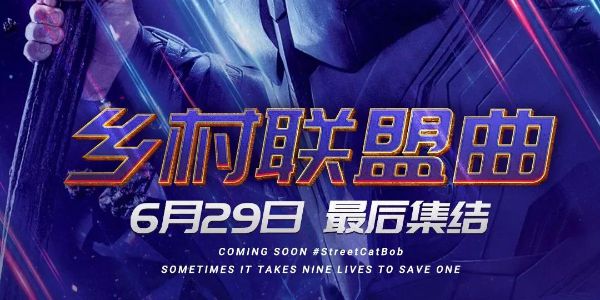
新媒体设计排版教程,新人必看的新媒体排版宝典
说到公众号排版,我认为这是每一位新媒体编辑必备的基本技能。
无论是在校社团新媒体小白,还是新媒体工作者,相信大家对排版界面都不会陌生,同样的一个界面,大家排版出来的效果却又千差万别。
去年陆续写过几篇关于公众号排版的文章,都深受小伙伴们喜欢,可惜没持续性为大家体系化整理,或许让一些小伙伴等得望眼欲穿。
过年期间开始准备了一段时间,写下这篇字数超1W字,干货知识点多达百个的长篇系列推文——《新媒体 · 公众号排版宝典》。
本篇长文,涉及公众号排版理论知识普及,推文排版参数标准,实用排版技巧及工具推荐四大板块,以供大家选择性的阅读查看。
01.
学习排版前,我们需要了解的东西
随着公众号的日益盛行,越来越多的企业在招聘的时候也增加了公众号编辑这一项工作要求,这也使得公众号编辑逐渐成为与office并肩,成为了日常工作中常用的一项办公技能。
很多人会说,公众号排版不就是将原有的Word文档,简单的复制粘贴到平台上而已吗?
但其实这个想法是错误的,新媒体编辑很多时候是兼顾内容、包装、原创及运营多个方面的一份工作。
以包装部分为例,主要工作就是为已有文案进行美化排版的过程,包括封面设计,文本排版、优化配图、banner、底部二维码、序号设计、分割线、历史原文等多个部分的排版。
公众号排版的作用
1. 保证推文美观流畅,减轻用户阅读压力。
用户阅读的时候往往是欣赏你的内容,但如果你的文章整篇都没有排版过,一长串密密麻麻,第一感觉会让人厌烦,没多少人会继续阅读下去。
2. 清晰传达文章有价值的信息,提高阅读效率
通篇文章如果没有将重点信息提取出来,用户阅读效率会很低,甚至容易错过关键信息,对标题、关键句等逻辑句进行排版,可以大大提高用户阅读效率。
3. 培养用户阅读习惯,加强对公众号品牌认知
我们每个人都会关注很多个公众号,如果每个推文的排版都千篇一律,那必然难以形成长远的品牌认知,但如果公众号能够提供给我们特定风格的排版,久而久之用户会产生依赖及习惯心理。
以一周进步、深夜发媸、杂乱无章为例,各自都有其特色的排版风格,对于用户而言会形成阅读习惯,阅读时会十分舒适。
一周进步主要内容为干货分享,图文以简约清晰排版,舒服地将实用内容传达给用户。
一周进步 · 排版样式
深夜发媸提供美妆时尚内容,排版风格往往设计感十足,从推文封面、内容排版到图片设计都充满了设计性,颜色往往比较吸引人,十分符合其平台定位。
深夜发媸 · 排版样式
杂乱无章的公众号排版,围绕主色调的蓝,文字做到清晰排版,很适合说故事表达观点,用户阅读下来没有太大压力。
杂乱无章 · 排版样式
通过优质的内容和独有的包装排版,能够让公众号在用户关注的同类型账号里形成独有的特色,从而提升整个公众号的形象。
排版前,需要思考的问题
公众号类型很多,所输出的内容也不一样,如果全部公众号都用统一的排版,那公众号便不存在“多样化”这一特性。
那么我们该如何优化公众号的排版呢,在这里我们可以问自己几个问题。
1. 你所需要排版的公众号是什么风格?
当我们需要优化一个公众号排版的时候,我们主要要考虑两个维度:行业和用户。
首先是行业,不同行业的公众号,在排版方面都会不太一样,从图片、文字到整体阅读体验,侧重点都因号而异。
a. 如果是干货类公众号,排版往往会选择清晰的简约设计,突出重点,主要用于图片设计与操作GIF设计。
b. 如果你是一个以故事、话题、观点为内容的账号,排版会更加文艺,字体会偏小,图片会采用影视截图及插画为主。
c. 如果你是一个资讯类公众号,排版会古朴官方,图片多采用新闻图片。
d. 如果你是一个漫画输出公众号,则更加要求排版的设计能力,往往需要专业的设计师、插画师耗费较长时间来完成。
用户角度,是排版者需要通过结合公众号用户群体进行调研结果而知的,将用户喜欢的内容,以更加新颖的形式传达,能够制造不少的爆点文章。
以当下很流行的漫画推文为例,文字读过了太多,做得非常好的公众号包括GQ实验室及不会画出版社。
GQ / 不会画出版社 · 排版样式
干货类公众号也是如此,以简洁的技巧介绍和详细的操作动图,传输有价值的内容。
一周进步 · 排版样式
2. 是否需要借助常规编辑器?
在一开始接触公众号的时候都会听到别人的的建议:百度找编辑器套模板编辑。
现在在百度上输入“公众号编辑器”,大概会出现上百种编辑器提供选择,很多小白在接触公众号排版的第一件事就是想着用第三方编辑器。
但现实是,目前发展得比较不错的公众号,往往都不采用第三方编辑器花里胡哨的排版,他们会有一套属于符合自己公众号特色的排版。
可以说,第三方编辑器正在慢慢成为了补充功能性排版工具,而非排版的主战场。
3. 你需要掌握什么技能?
从事公众号编辑,你需要完成对文字,图片的优化处理,所以你需要具备一定的审美能力、软件运用、探索自学能力。
审美·能力,排版是一个需要反复预览的过程,站在读者的角度阅读文章,看看阅读起来舒不舒服,因此要有一个自己对“排版好看”的定义。
软件运用能力,新媒体编辑一定程度上需要掌握多种软件的运用,包括图片处理、音频简单剪辑、各种用户交互工具的运用,主要使用软件在后文提供介绍。
探索自学能力,日常看到优质的排版案例,必须保持积累和学习更多排版方式,利用碎片收藏和定期整理,掌握其排版思路和工具使用,以此借鉴优化。
02.
公众号排版的组成部分及参数设置
了解完公众号排版的一些偏理论性的知识普及以后,接下来为大家介绍实打实的公众号排版组成部分及参数设置。
排版组成
正常工作分工下,一篇推文的排版需要完成内包装及外包装两个部分,外包装包括推文的封面和标题摘要,内包装则包括了顶部图片、正文排版和尾部组件三个部分。
封面设计,推文的门面。
作为推文的门面,每条推送的封面,其实很多时候也是编辑自己完成的,因此掌握PS或者第三方制图网站显得非常重要。
封面图的作用,主要有两个。
① 吸引用户打开率
信息流下的推文浏览,更加看重封面图与标题是否吸引用户点击,一张优秀的封面图已经在订阅号界面领先了一大半。
② 增强设计统一性
公众号推文封面作为日常更新的门面,统一的封面设计风格有利于增强公众号的统一性。
封面图设计注意要点
其中,用户在订阅号界面接收推送封面图,主要有三种形式。
星标 / 常阅公众号 / 一般公众号。
星标指的是用户对公众号进行置顶的一个造作,常阅公众号由系统自动识别,以上两者推送的封面图,我们可以接收全图的尺寸,而一般公众号,我们只能够接收到正方形小图封面。
去年信息流更新后,推文封面图在短时间内更新了5次,好消息是2019以来的:近期封面图,没有更新,版式尺寸也趋于稳定统一。
目前微信推送的封面预览形式最终为以下的格式:
公众号封面图片尺寸比例是2.35:1,原版默认16:9的尺寸必须通过裁剪封面,才能得到正确尺寸的封面,要注意的是1:1比例的封面设置,必须尽可能将重点展现给用户。
具体参数见后
由于当前封面的组成并不只有封面图,文字阴影及阅读人数的显示,也会影响着封面信息传达的效果,我们需要对此做标题、图片、星标三者同时进行适配,这里给大家分享几招。
a. 控制字数
推文标题最多可以输入64个中文字符,但我们在取标题的时候只要把重要信息放置在封面即可,数量控制在20字内最佳。
按照惯例,我们拆解几个公众号的封面图设计风格我们可以得到一些规律。
利用优质的图片,配合上公众号LOGO及关键字句的形式,能够做出美观的封面。
b. 用好图片,少用文字
封面版式面积变小,受标题阴影影响,封面可设计空间已经很小,倒不如直接使用符合推文的优质图片,简单带上公众号LOGO即可。
优质的图片一般都有这两个特点:
高清,无版权可商用
I. 高清
普遍搜索到的图片清晰度总是不怎么让人满意,过于小的图片放大之后模糊会让人有种不安全感,并且无法进行结合排版处理的更加美观,所以我们需要高清图片。
II. 无版权可商用
百度,搜狗之类的常用搜索引擎,搜索出来的图片往往都携带着版权,如果不经过商用授权直接使用,在国家越来越重视版权的前提下,赔偿额也愈发触目惊心。
所以,我们需要使用遵循CC0协议的无版权可商用的高清图片。
用好图尤为重要,过往介绍过很多网站,在后文也会提供相关可商用图片版权。
C. 提醒星标
再次强调星标,有星标与无星标对封面的阅读有非常大的关系,星标能够看到整张设计的封面图,能够大大提高打开率。
文本排版,简洁而流畅。
文字部分,占据了推文80%以上的内容,可以有很多种排版参数可以选择,包括了文字字体、大小、颜色、形态、对齐、以及特殊符合等多种排版。
① 字体
一般情况下,排版推文的字体是默认字体,中规中矩,但其实推文的字体也是可以调整的。
在公众号编辑器或第三方编辑器中,在字体选择处,我们可以选择除了默认字体外多种字体格式,其中实用频率最高的是:Optima-Regular(中文细体)。
水韬呀 / 槽值 · 排版样式
至于具体字体大小,建议正文取14-16为最佳选择。
14号字体偏小,比较文艺清新;
15号字体中规中矩,看着舒服;
16号字体为默认大小,适合官方的公众号。
② 形态
和word编辑一样,公众号文字形态也可以做一些基本变化,例如底色填充,加粗、斜体、下划线、删除线等,常用的是加粗,以及有趣(戏多)的删除线。
利用形态的改变,适当使用可以丰富枯燥单一的排版。
以底色填充和斜体为例,在公众号中利用底色填充和斜体进行排版,在视觉上会形成一个很好的突出及过渡效果。
浪潮工作室 / 杂乱无章 · 排版样式
③ 颜色
排版文本的时候,要注意颜色搭配。
主要遵循两个原则:大体保持统一,个别使用特殊色强调。
字体颜色尽量不超过三种,颜色不要选取太亮的颜色,例如纯黑,纯红,亮红配亮绿,都是不建议的,看久了眼睛难免会疲惫,不利于阅读。
建议使用字体颜色:
标题:使用公众号常用色,或者logo或行业色
正文:选择亮度没这么高的字体,这是纯黑 #000000#,比较偏灰会更加适合阅读#595757# #3f3f3f# 等
批注:选择比正文亮度还低,更加浅的浅灰色,例如 #595959# #888888# #d6d6d6#
P.s:一篇推文尽量不要超过 3 种颜色
结合以上几点,我们可以将一段干巴巴的内容,完成基本的美化排版。
在公众号排版后台,我们首选公众号主题色作为推文的特殊色,另外也可以自定义输入颜色色号进行字体填充。
真的要每一步进行实操与测试,相信要花上一段时间,但如果你都能够全部都吸收,相信你一定能吸收到很多,能够独立且高效完成公众号排版。